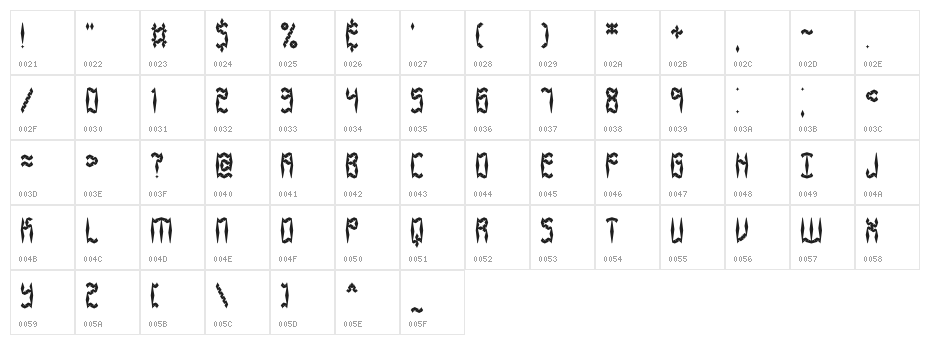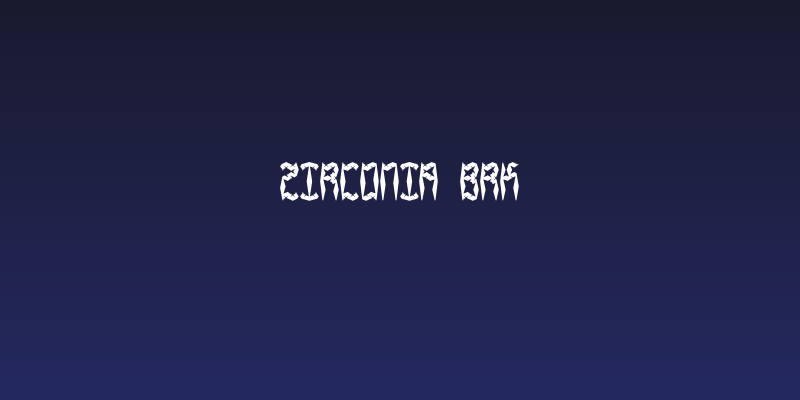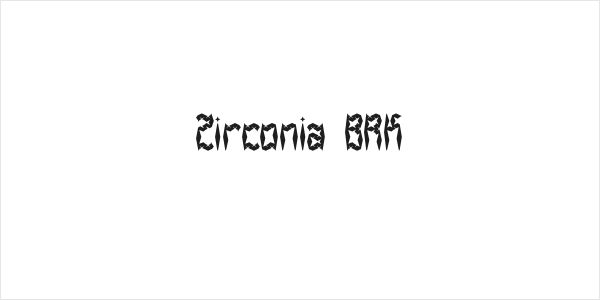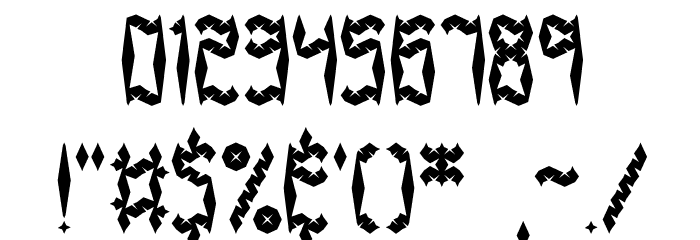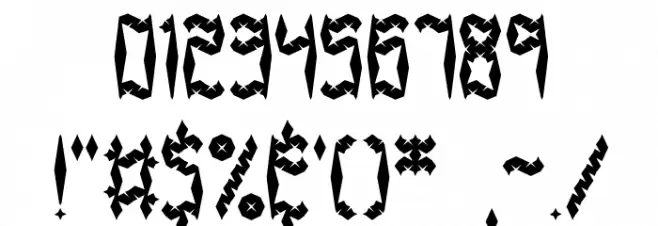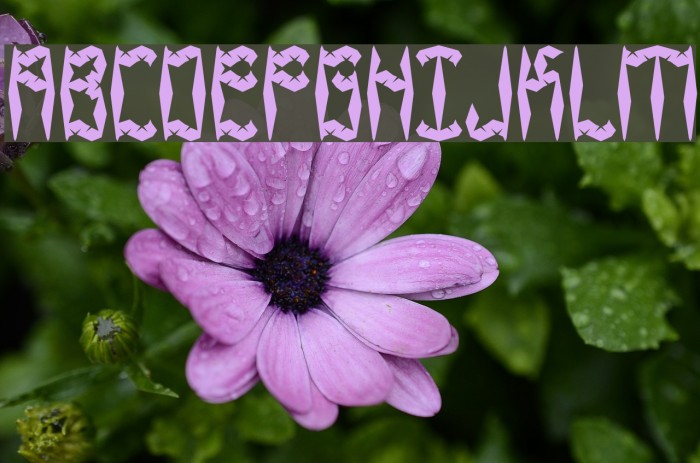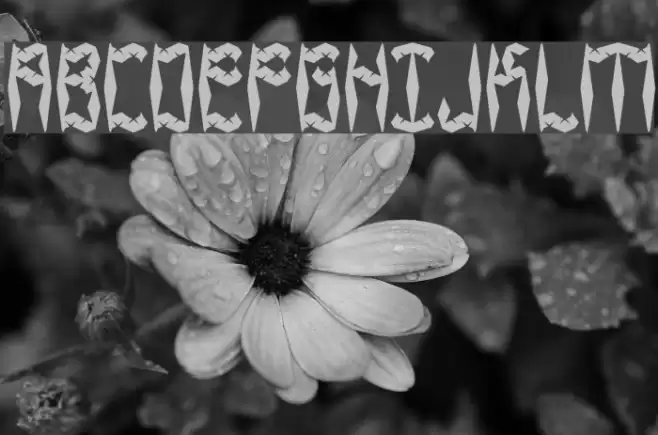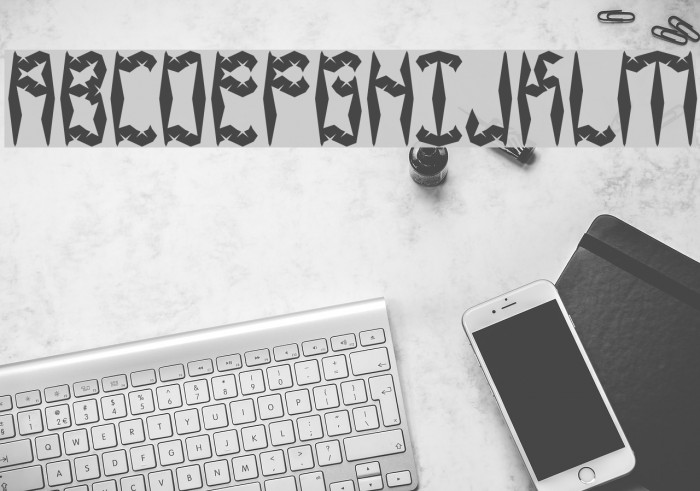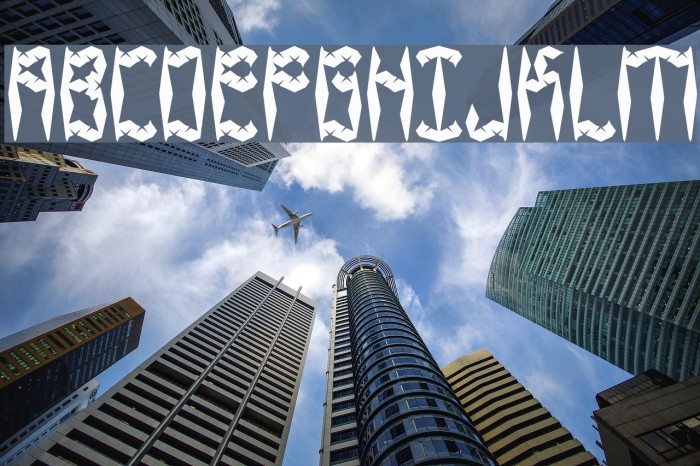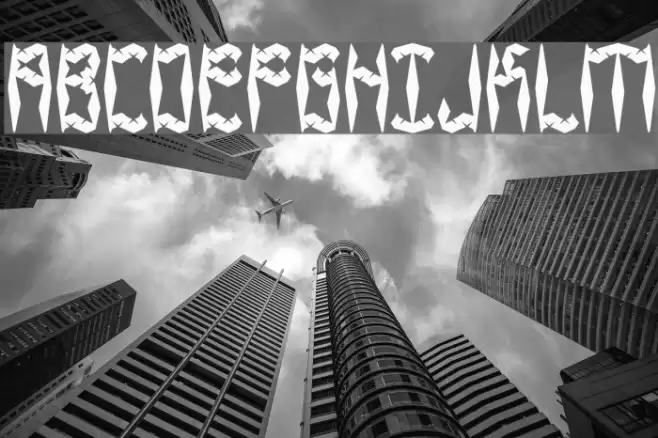
Zirconia BRK Font
| Vorgeschlagene Projekte | Ideal for album covers, posters, branding for edgy or modern products, and any design that requires a standout, artistic font. |